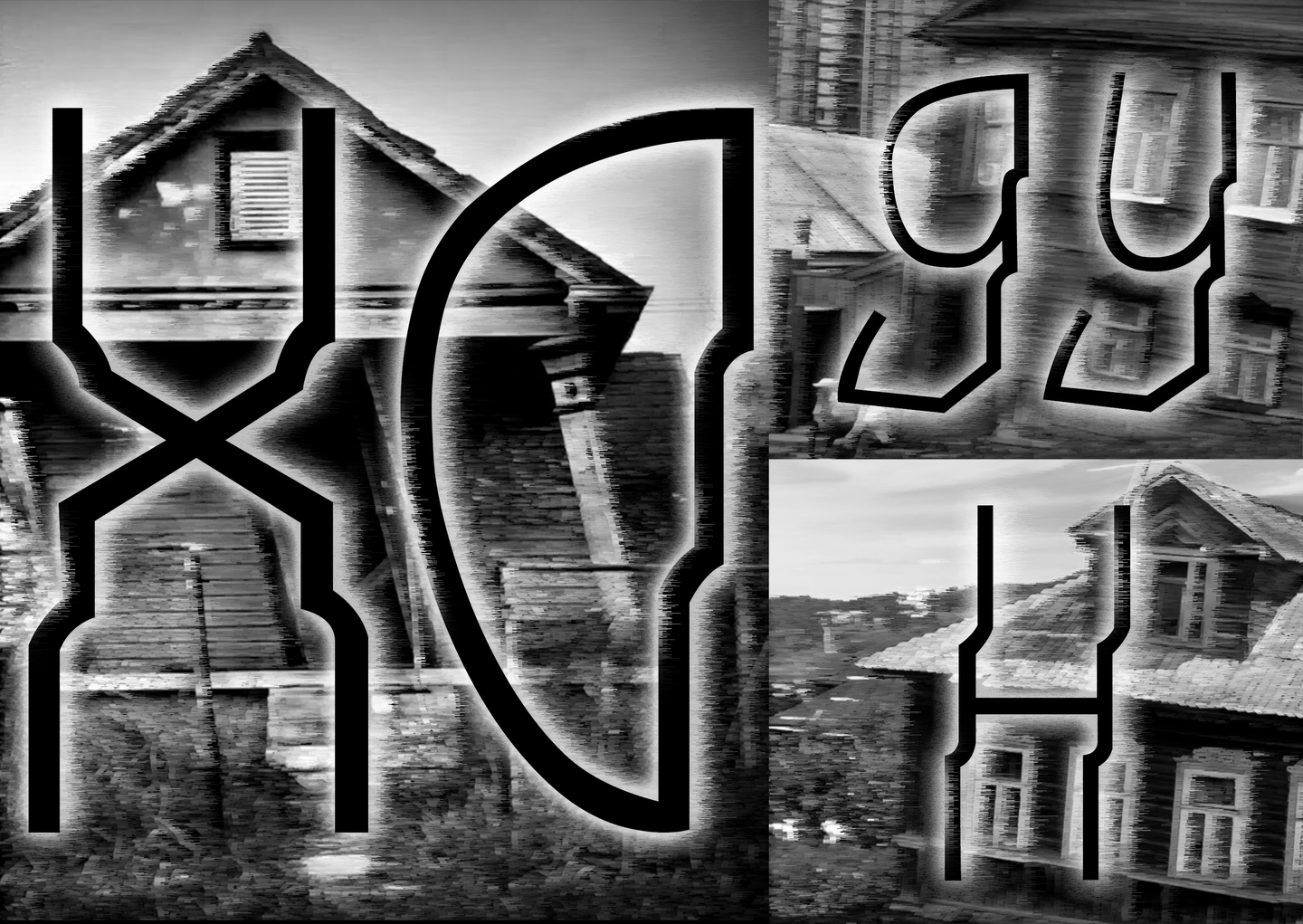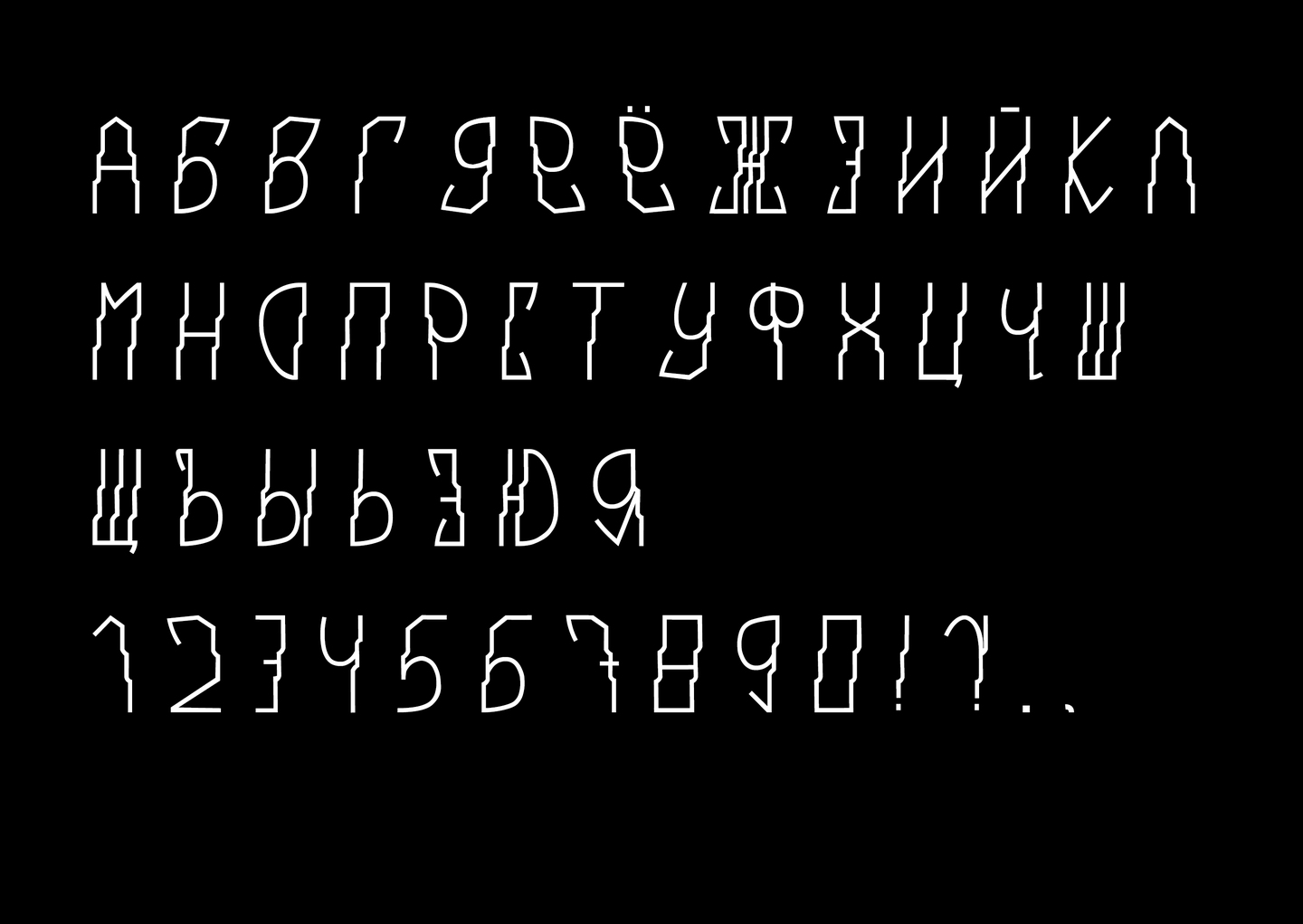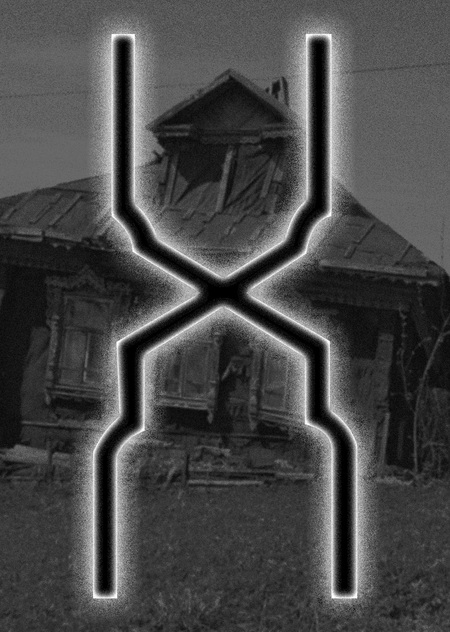
Шрифт «Ходун»
Шрифт был нарисован в марте 2023 года на интенсиве от Словолитни Шрифтовик.
Идея шрифта родилась из обыкновенной вещицы — маленького мультитула. Его формы всегда казались мне интересными и я решил переосмыслить их в своем шрифте.
В итоге буквы получились похожими на старые покосившиеся дома, которые еле-еле стояли и от своей ветхости заваливались вбок, «ходили ходуном». Отсюда и такое название шрифта.
Конечно, шрифт вышел таким, как вы увидели выше, не сразу.
Первый вариант был достаточно сумбурным и я отправился его переделывать.
Вот так изменились буквы. Количество используемых элементов было сокращено, плюс я начал следовать более строгой логике их использования, что поспособствовало цельности гарнитуры
Были добавлены лигатуры и вариации для нескольких символов.
В итоге получился самобытный акцидентный шрифт, с нотками фольклорных мотивов, конструктивизма и цифровой эстетики одновременно.